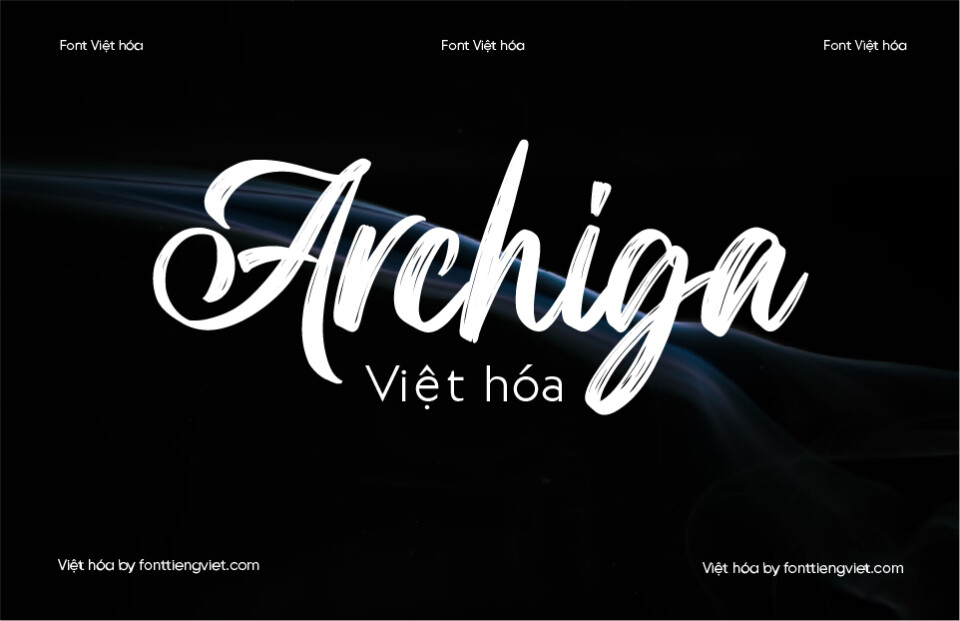
Đánh Giá Chi Tiết Font Việt hóa 1FTV VIP Archiga – Brush: Tuyệt Phẩm Typography Cho Học Sinh Và Nhà Thiết Kế
Trong thế giới thiết kế đồ họa và sáng tạo nội dung, việc tìm kiếm một bộ Font Chữ độc đáo, chất lượng cao và đã được Việt hóa hoàn chỉnh luôn là ưu tiên hàng đầu. Hôm nay, chúng ta sẽ đi sâu vào tìm hiểu về một siêu phẩm đang làm mưa làm gió trong cộng đồng designer: Font Việt hóa 1FTV VIP Archiga – Brush. Đây không chỉ là một phông chữ (typeface) thông thường; nó là sự kết hợp hoàn hảo giữa nét cọ nghệ thuật (brush style) và tính ứng dụng thực tiễn, đặc biệt phù hợp cho các dự án của học sinh, sinh viên và những người đang chuẩn bị cho các kỳ thi tốt nghiệp cần sự nổi bật về mặt trình bày.
Giới Thiệu Về Font Việt hóa 1FTV VIP Archiga – Brush
Bộ phông chữ Archiga nguyên bản vốn đã nổi tiếng với phong cách viết tay mạnh mẽ, giàu cảm xúc. Tuy nhiên, phiên bản Font Việt hóa 1FTV VIP Archiga – Brush đã nâng tầm giá trị này lên một cấp độ mới. Việc Việt hóa không chỉ đơn thuần là thêm các dấu câu, mà còn tối ưu hóa về mặt khoảng cách, đường nét để đảm bảo khi sử dụng tiếng Việt, phông chữ vẫn giữ được vẻ đẹp tự nhiên và tính thẩm mỹ cao nhất. Sự khác biệt lớn nhất nằm ở tính “VIP” – thường ám chỉ chất lượng hoàn thiện cao cấp, được tinh chỉnh kỹ lưỡng, rất cần thiết cho các tài liệu in ấn hay các bài thuyết trình quan trọng của học sinh cấp 3.
Đặc Điểm Nổi Bật Của Phông Chữ Brush Sáng Tạo
Archiga – Brush thuộc nhóm font script/handwriting, mô phỏng lại những nét cọ vẽ nhanh, tạo cảm giác tự do và phá cách. Điều này làm cho nó trở thành công cụ lý tưởng cho các poster, bìa sách, tiêu đề bài luận sáng tạo, hay thậm chí là các dự án kỷ yếu tốt nghiệp. Các đặc điểm kỹ thuật nổi bật bao gồm:
- Tính Nghệ Thuật Cao: Các nét chữ dày, mỏng đan xen một cách tự nhiên, mô phỏng chân thực cảm giác của việc viết bằng bút lông hoặc cọ vẽ.
- Hỗ Trợ Tiếng Việt Toàn Diện: Đây là yếu tố then chốt. Sự Việt hóa chất lượng cao đảm bảo không có lỗi hiển thị dấu câu hay khoảng cách bị lệch, một vấn đề phổ biến ở các font nước ngoài chưa được tối ưu.
- Phù Hợp Với Typography Hiện Đại: Font này dễ dàng kết hợp với các phông chữ Sans-serif đơn giản khác để tạo ra sự tương phản hấp dẫn trong thiết kế.
Ứng Dụng Thực Tiễn Trong Học Tập và Đồ Họa
Đối với học sinh và sinh viên, việc trình bày bài tập hay dự án khóa học không chỉ cần nội dung tốt mà còn cần hình thức thu hút. Font Việt hóa 1FTV VIP Archiga – Brush cung cấp một giải pháp hoàn hảo để làm nổi bật tiêu đề, các trích dẫn quan trọng, hoặc tạo logo cá nhân cho các câu lạc bộ (CLB) học thuật.
Việc sử dụng một phông chữ chất lượng, đã được Việt hóa kỹ lưỡng như Archiga giúp tiết kiệm thời gian chỉnh sửa lỗi font, cho phép người dùng tập trung hơn vào nội dung cốt lõi. Trong bối cảnh các kỳ thi tốt nghiệp hay các buổi bảo vệ dự án cuối cấp yêu cầu tính sáng tạo, phông chữ này chính là vũ khí bí mật giúp bài làm của bạn để lại ấn tượng mạnh mẽ.
Lợi Ích Khi Sử Dụng Phiên Bản Việt Hóa Chất Lượng Cao (1FTV VIP)
Cụm từ “Việt hóa 1FTV VIP” ám chỉ rằng phông chữ đã trải qua quá trình chỉnh sửa chuyên sâu bởi team 1FTV, đảm bảo chất lượng kỹ thuật cao nhất. Sự khác biệt giữa một font thông thường và một font VIP nằm ở chi tiết, đặc biệt là các ký tự mở rộng (Glyphs) và sự đồng nhất về nét thanh, nét đậm khi gõ tiếng Việt. Đối với các ấn phẩm học thuật hoặc các tài liệu chính thức cần in ấn, độ tin cậy của font Việt hóa chất lượng cao là cực kỳ quan trọng.
Sử dụng Archiga – Brush trong các dự án thiết kế liên quan đến trường học, như thiệp mời sự kiện, áo đồng phục lớp, hay slide thuyết trình, giúp truyền tải thông điệp một cách năng động và trẻ trung. Đây là sự lựa chọn tuyệt vời để thoát khỏi sự nhàm chán của các phông chữ hệ thống như Times New Roman hay Arial, mang lại cá tính riêng cho người sử dụng, từ đó nâng cao chất lượng tổng thể của sản phẩm đồ họa.
Lý Do 1FTV VIP Archiga Là Lựa Chọn Hàng Đầu Cho Các Dự Án Sáng Tạo
- Tối Ưu Hóa Tốc Độ Thiết Kế: Với bản Việt hóa hoàn chỉnh, bạn chỉ cần cài đặt và sử dụng mà không cần lo lắng về việc căn chỉnh dấu hay thiếu ký tự.
- Tương Thích Đa Nền Tảng: Phông chữ này thường tương thích tốt trên nhiều hệ điều hành và phần mềm thiết kế phổ biến như Adobe Photoshop, Illustrator, và các công cụ trình chiếu (PowerPoint, Keynote).
- Tạo Dấu Ấn Cá Nhân: Phông chữ Brush mang tính cá nhân hóa rất cao, là công cụ không thể thiếu khi xây dựng thương hiệu cá nhân (personal branding) cho sinh viên hay các dự án khởi nghiệp nhỏ.
Hãy tưởng tượng bạn đang thiết kế bìa kỷ yếu hoặc một lời chúc tốt nghiệp. Việc sử dụng một phông chữ viết tay, đậm chất nghệ thuật như Archiga sẽ tạo ra sự khác biệt lớn so với việc dùng các phông chữ máy móc. Đây là bí quyết giúp các tác phẩm của bạn đạt điểm cao hơn về mặt thẩm mỹ trong mắt giáo viên và ban giám khảo.
Đặc biệt, trong quá trình ôn luyện cho các kỳ thi quan trọng như thi tốt nghiệp THPT, đôi khi việc thiết kế các bản tóm tắt kiến thức (mind maps) bằng hình ảnh và typography độc đáo cũng giúp quá trình ghi nhớ trở nên hiệu quả hơn. Phông chữ này hỗ trợ đắc lực cho mọi hoạt động sáng tạo từ đơn giản đến phức tạp.
Tóm lại, Font Việt hóa 1FTV VIP Archiga – Brush là một tài sản vô giá cho bất kỳ ai hoạt động trong lĩnh vực thiết kế hoặc cần sự sáng tạo trong học tập. Với chất lượng Việt hóa tuyệt vời, phong cách nghệ thuật độc đáo và tính ứng dụng cao, nó xứng đáng là một trong những phông chữ brush hàng đầu hiện nay. Việc sở hữu và sử dụng bộ Font Chữ chất lượng này không chỉ nâng cao tính chuyên nghiệp của các dự án mà còn thể hiện gu thẩm mỹ tinh tế của người dùng. Đừng ngần ngại khám phá và áp dụng Archiga – Brush vào các dự án tiếp theo của bạn!